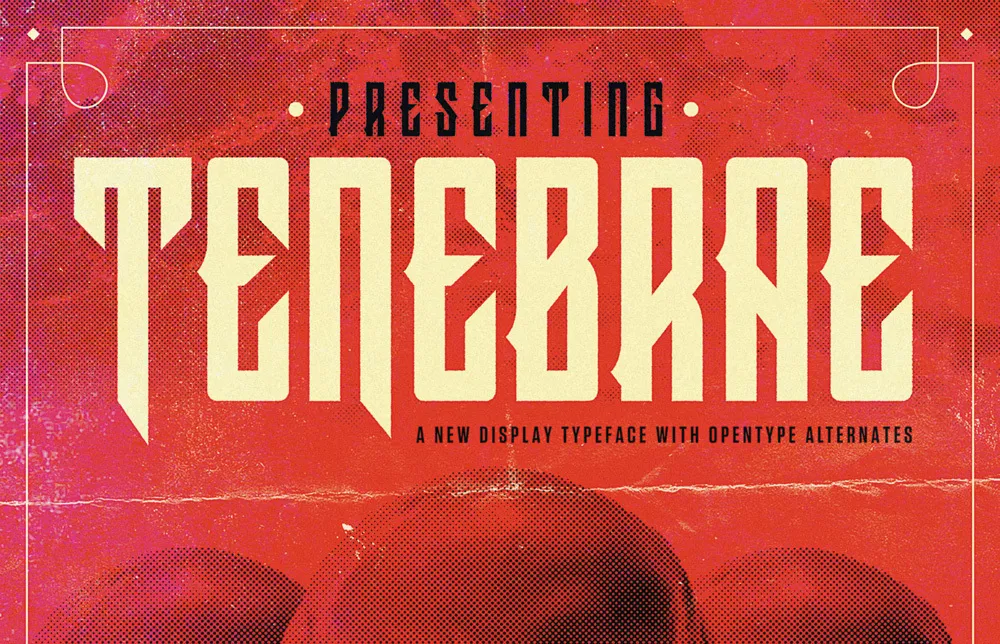
Tenebrae é uma tipografia sans-serif inspirada nos estilos cinematográficos do giallo da década de 70 e das posters de filmes cult. Embora suas origens sejam nessas atmosférias sombrias e excêntricas, Tenebrae mantém um toque moderno que a faz adaptável tanto para ambientes vintage quanto para os mais atuais. Um destaque desta fonte é o uso de alternativas em título, que conferem à letra uma personalidade ainda mais expressiva. Perfeita para gráficos com apelo visual e arrojado, Tenebrae oferece uma maneira única de dar um toque moderno a textos clássicos ou históricos sem desgastar o olhar do espectador. Seja em uma loja antiga cheia de livros de horror ou na capa de um livro de literatura contemporânea, Tenebrae é uma escolha inteligente para ilustrar seus designs.